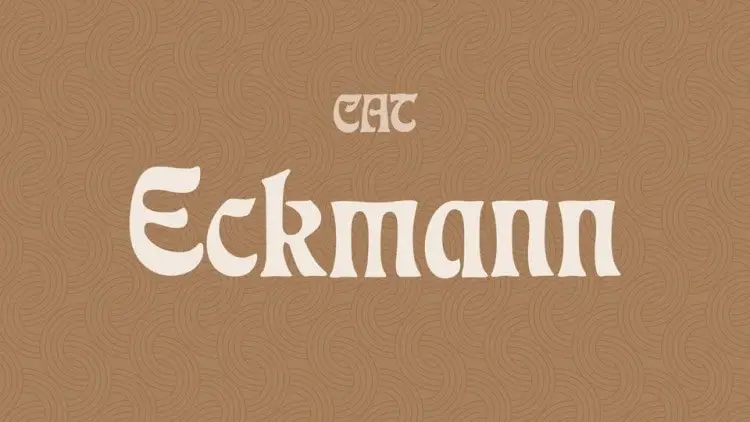
A CAT Eckmann Display Font é uma tipografia para uso em exibição que transmite a elegância e a fluididade do Art Nouveau, baseada no desenho inspirado por Otto Eckmann. Essa fonte traz um sabor inconfundível de Fraktur, oferecendo aos designers incríveis oportunidades para criar designs belos e únicos. Perfeito tanto para nomes, quanto para headlines em banners ou revistas, a CAT Eckmann Display Font se destaca por sua versatilidade e facilidade de uso, tornando-a uma escolha ótima para quem deseja destacar seus projetos com um estilo elegante e contemporâneo. Engane-se ao não incluir essa fonte em seu próximo projeto que exige design em grande escala ou requere a criação de designs memoráveis.